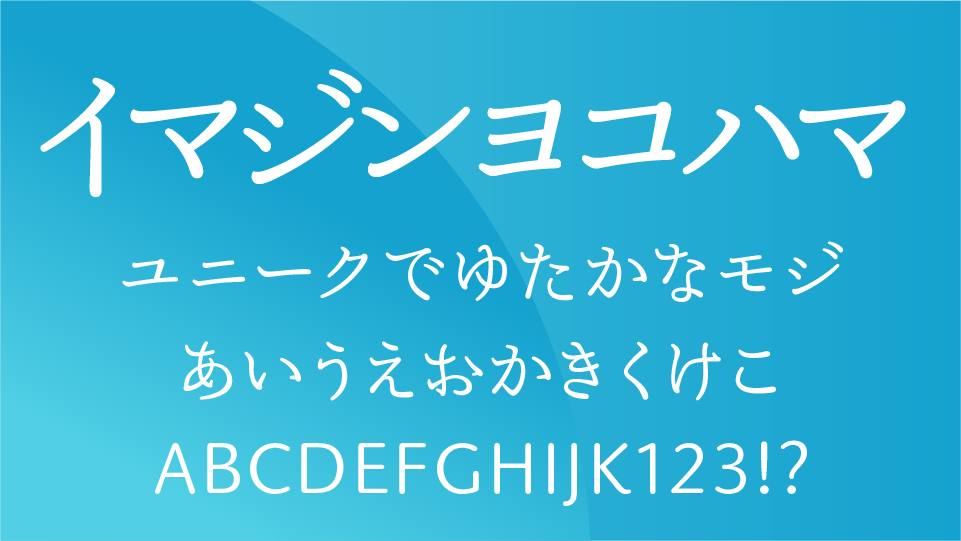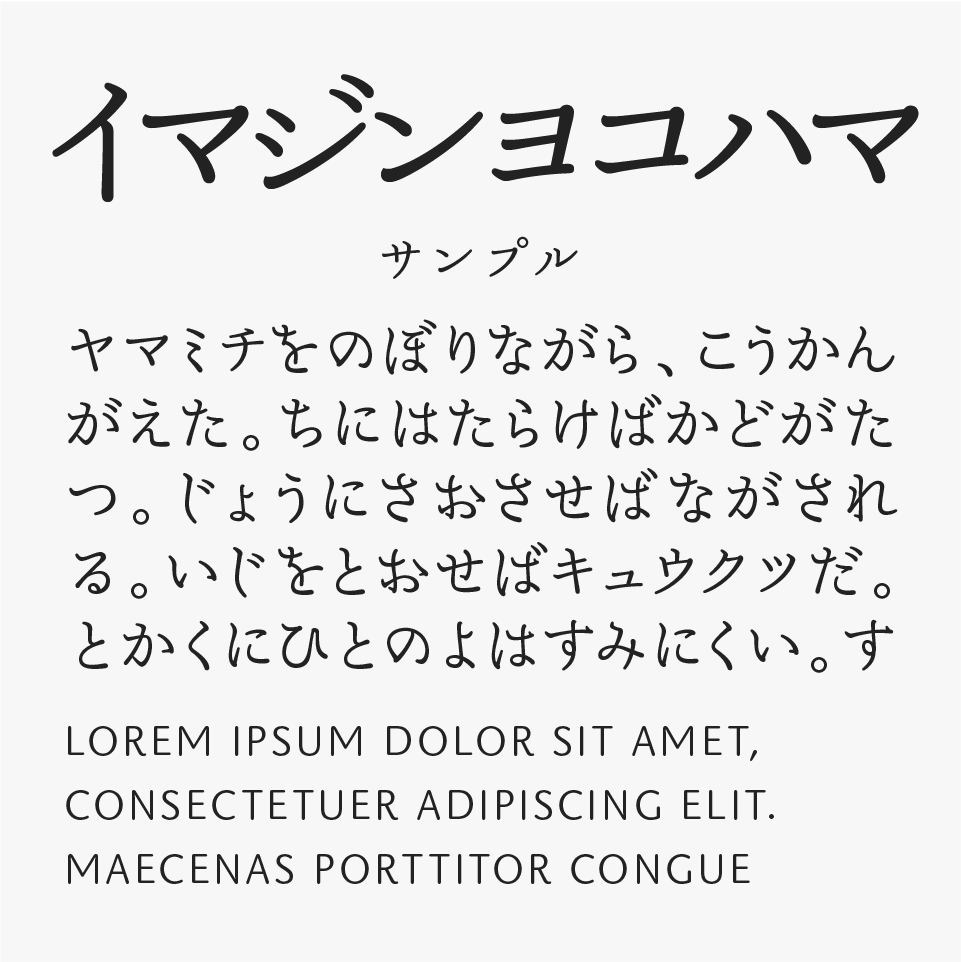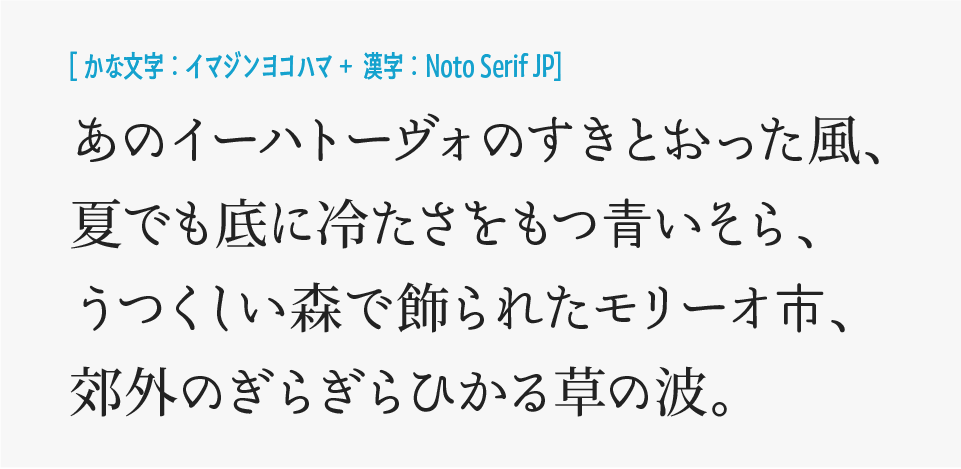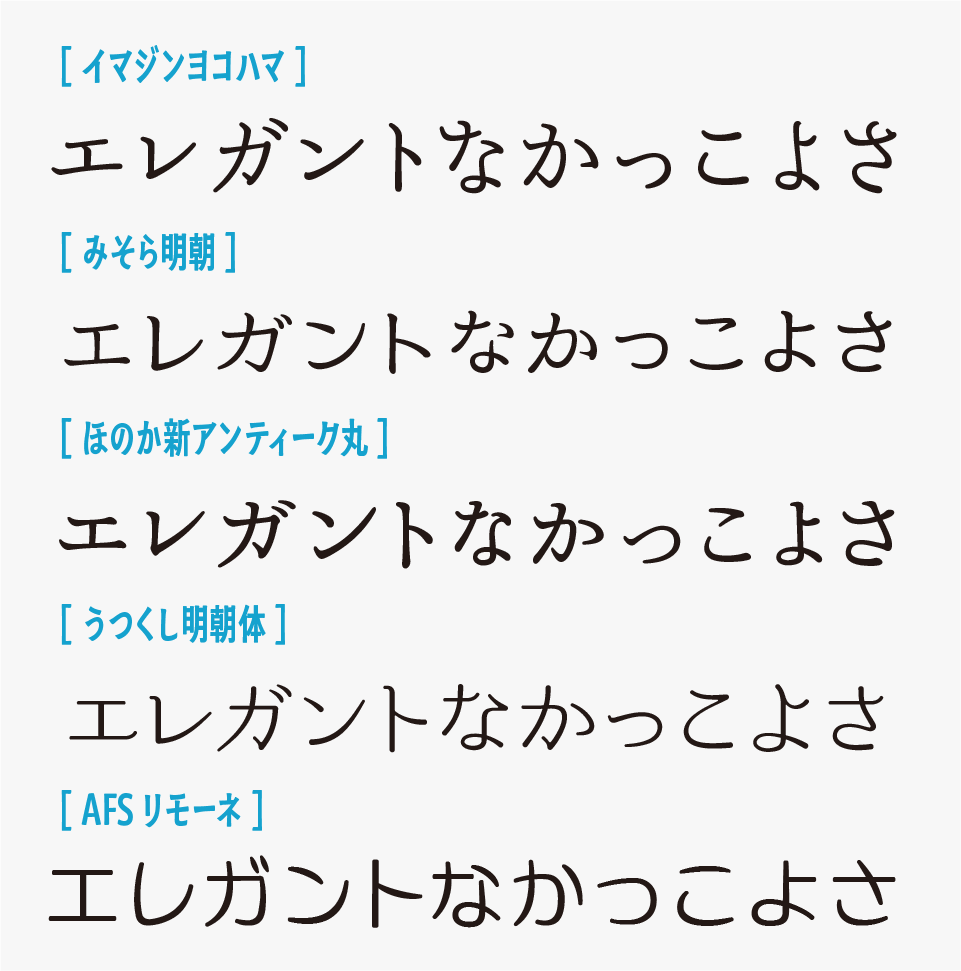
イマジンヨコハマ
イマジンヨコハマフォントは、横浜市のイメージコレクターズの活動の中で集められた横浜のイメージから連想し制作された、細身でゆったりしたデザインフォントです。
横浜が連想されるような都会的で落ち着いた空気感が感じられるようなフォントです。行政がフォントを制作して、配布されているのは面白い取り組みですね。
レトロな雰囲気をほのかに感じさせながらも古さを感じさせず、現代的なデザインにも自然に馴染む上品なフォントです。
ファッションやライフスタイル系のデザイン、カフェ、雑誌、ポスター、などにぴったりなフォントです。静かで洗練された存在感があるため、情報をすっきりと見せたい場面や、大人っぽくスタイリッシュな雰囲気を表現したいデザインで活躍してくれるフォントです。
漢字は、「横浜市」と横浜18区の区名に使われる文字のみを収録しています。長文で使用する場合は、別フォントと混植すると使いやすくなります。サンプルでは「Noto Serif」と組み合わせています。
イマジンヨコハマフォントを、ほかのやわらかく美しい雰囲気を持つフォントと比較してみると、 横画やはらいをすっきりと抑えた端正なデザインが特徴的で、派手に個性を主張するというよりも、上品で落ち着いた印象が感じられるフォントとなっています。
収録文字は、漢字(「横浜市」と横浜18区の区名に使われる文字)・ひらがな・カタカナ・アルファベット・数字・記号が収録されています。